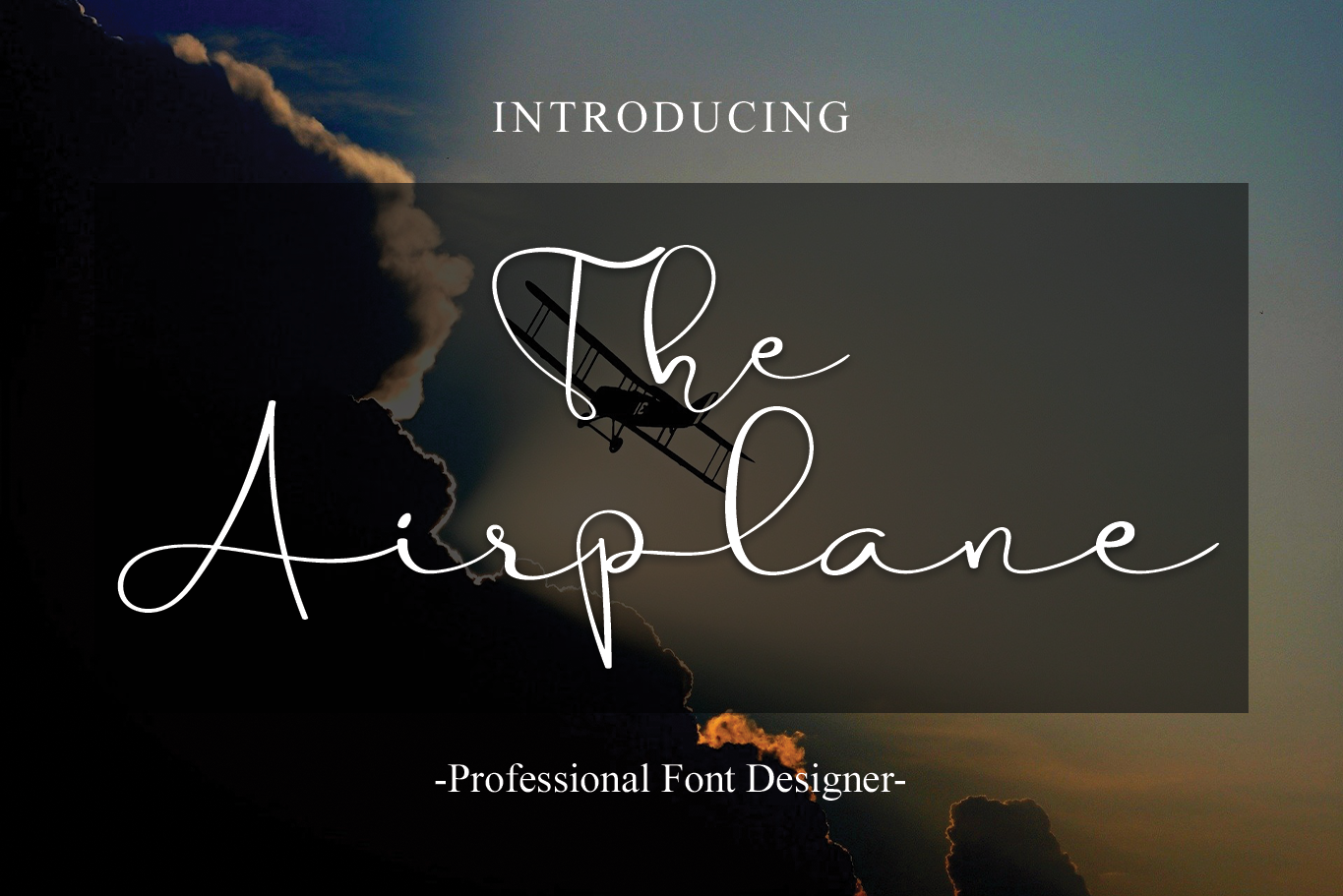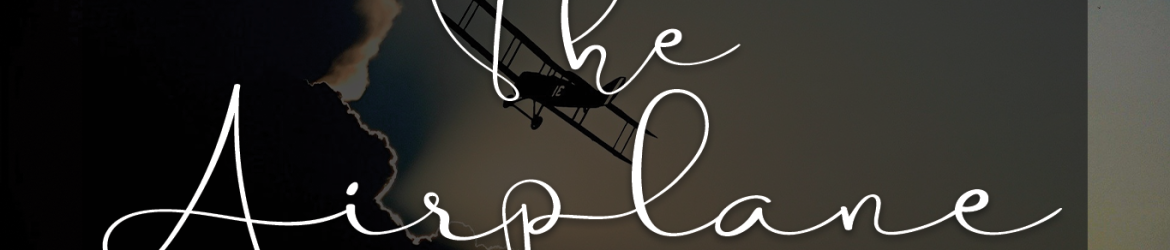
The Airplane Font – Download Grátis
Esta é uma fonte escrita a mão, perfeita para aqueles que buscam algo elegante e fluido. Seu design delicado transmite elegância através de cada traço, tornando-a ideal para uso em cartões de casamento, cartas de agradecimento, citações, cartões de boas-vindas, logotipos, cartões de visita e em qualquer outro tipo de design que deseje dar um toque único. Com certeza, The Airplane Font é perfeita para personalizar seus documentos de uma maneira única e sofisticada, tornando seu trabalho ainda mais especial. Esse fonte ficará perfeitamente à vontade no seu próximo projeto gráfico.